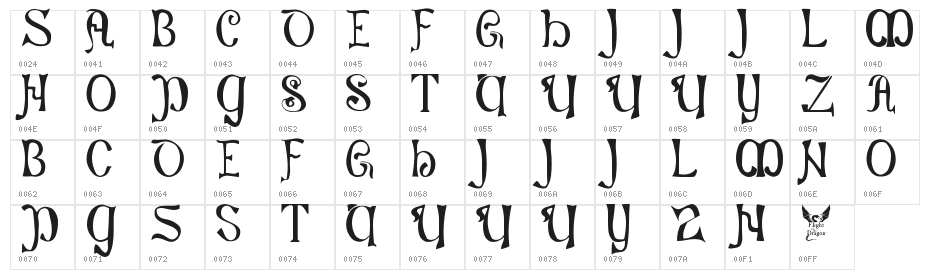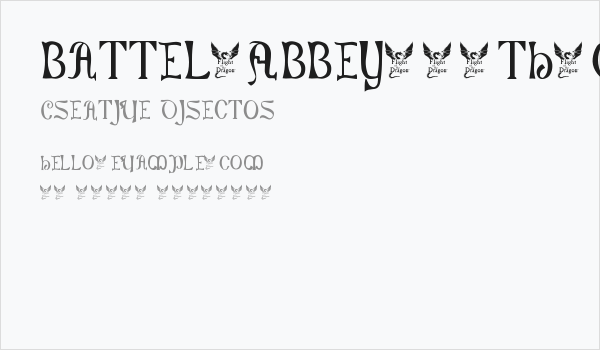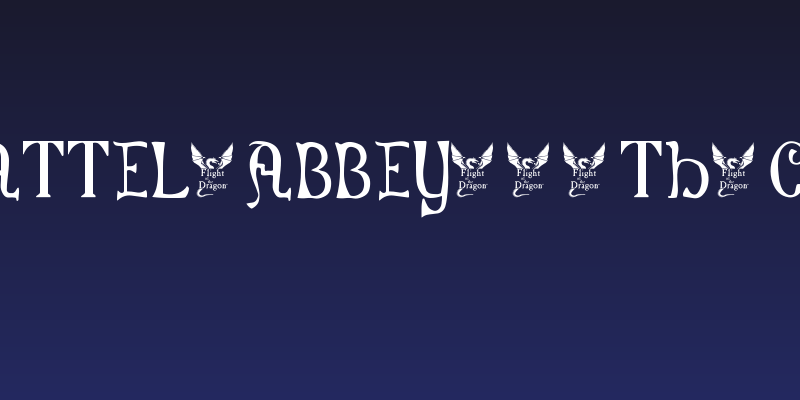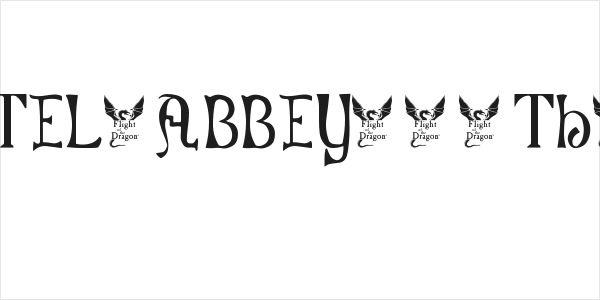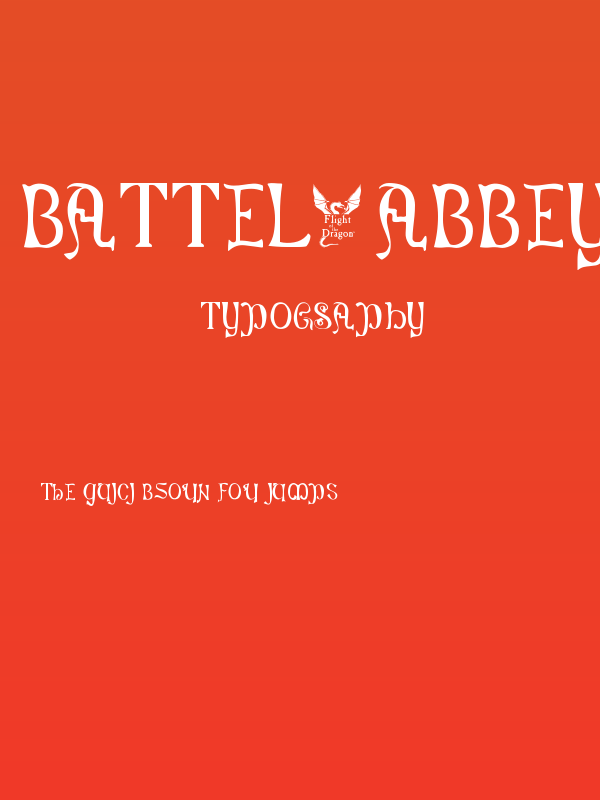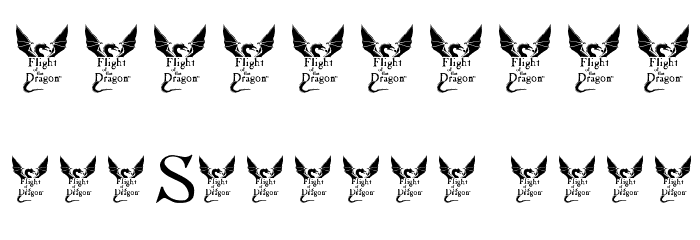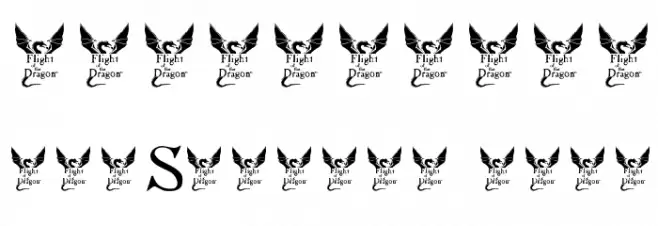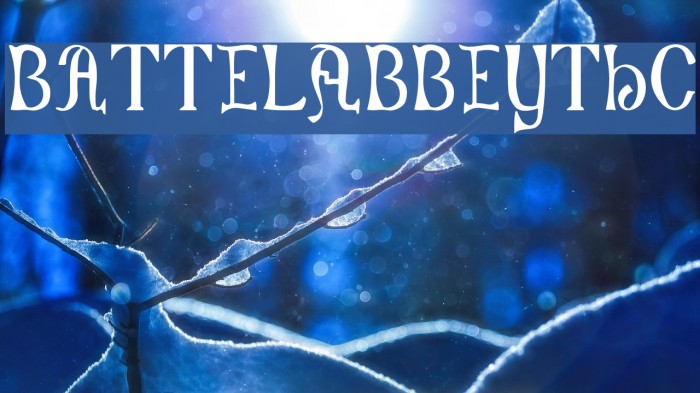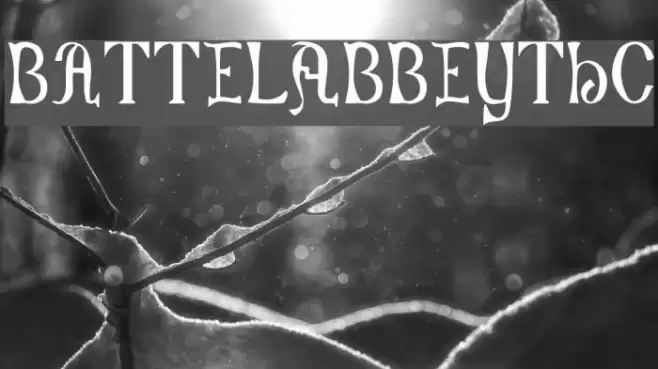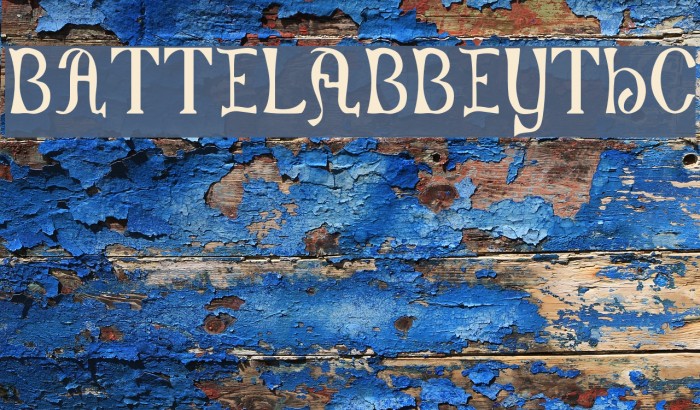
Battel-Abbey--8th-c- Font
| Estilo general | Gothic, Medieval |
| Proyectos propuestos | Ideal for historical or fantasy-themed projects, such as book covers, posters, or video game titles. |